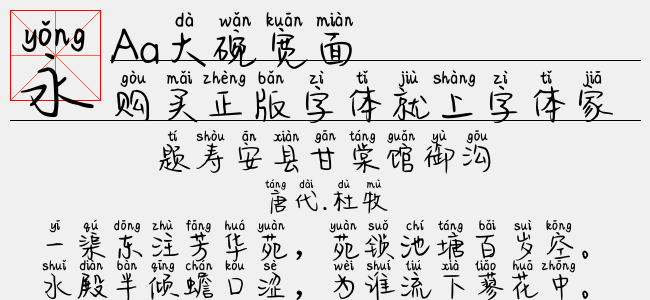
Aa大碗宽面-Aa字体
Aa大碗宽面是一款大小6.09 M的Aa字体字体,主要特征是手写,拼音体,手书风格,行书,,Aa大碗宽面为TTF格式的文件,采用安装嵌入,包含了英文、拉丁文以及日文等符号,字宽中等(正常),当前版本是Version 1.000,共计6763个汉字以及附加其他英文字体和阿拉伯数字。
字体作者:Aa字体
字体名称:Aa大碗宽面